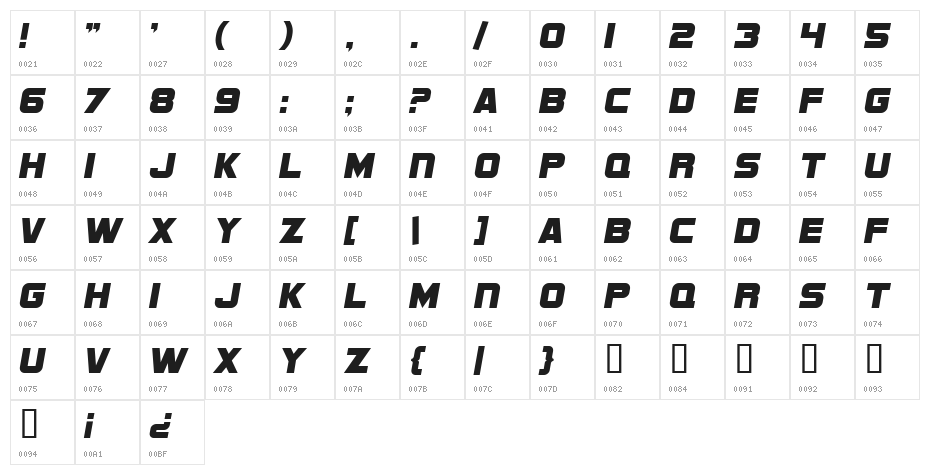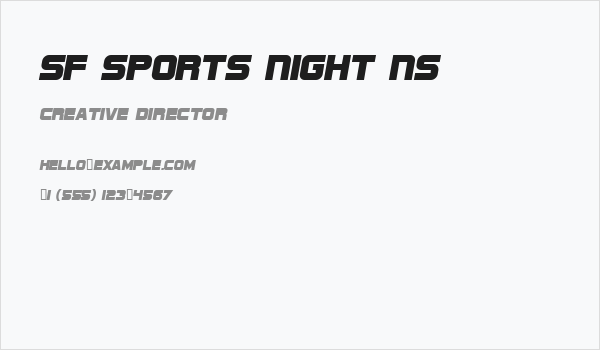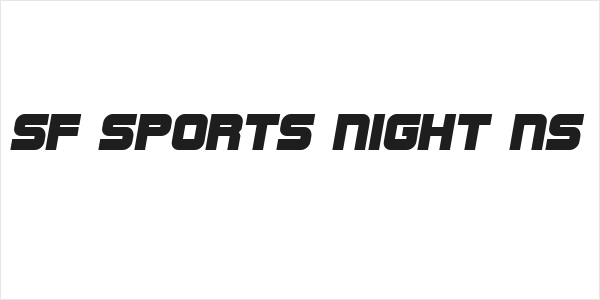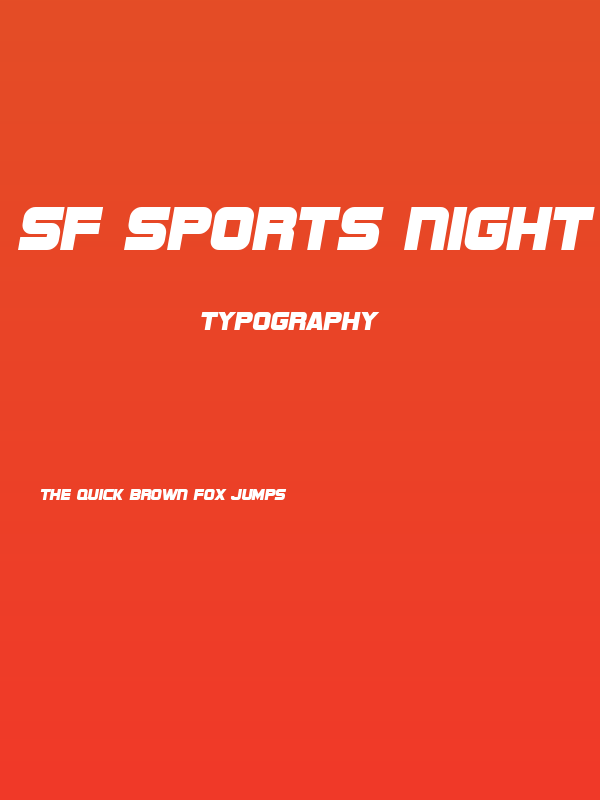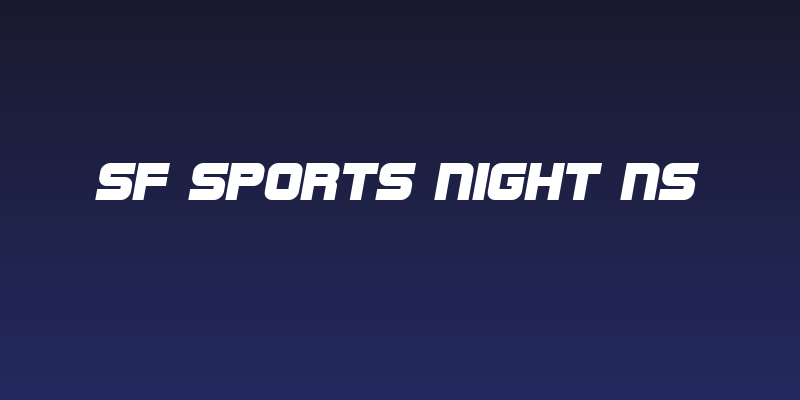
SF Sports Night NS Font
| Anwendungsfall | Headlines, Logos, Sports branding |
| Vorgeschlagene Projekte | Ideal for sports branding, event posters, team jerseys, and dynamic advertising campaigns. |